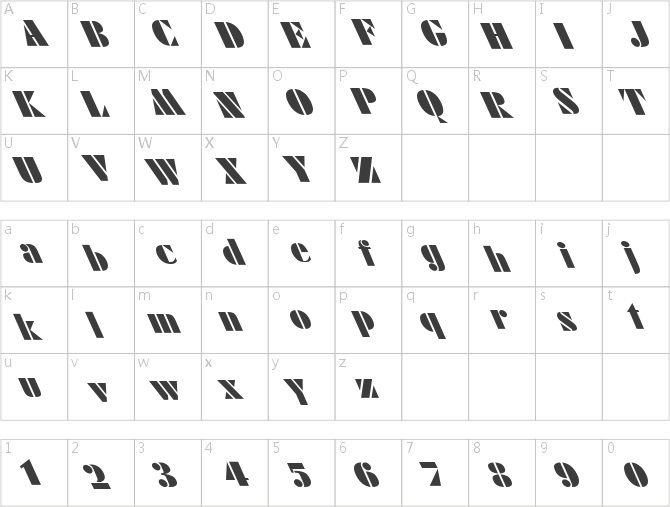
Futuri-Black-Leftified at Night 详情页
Futuri-Black-Leftified at Night
Futuri-Black-Leftified at Night字体字库是一款让人赏心悦目、百看不厌的英文字体,适合各类广告和产品包装设计应用,字体大小0.03MB,格式为ttf字体,上传用户是昊天金诚,作者/版权方为未知